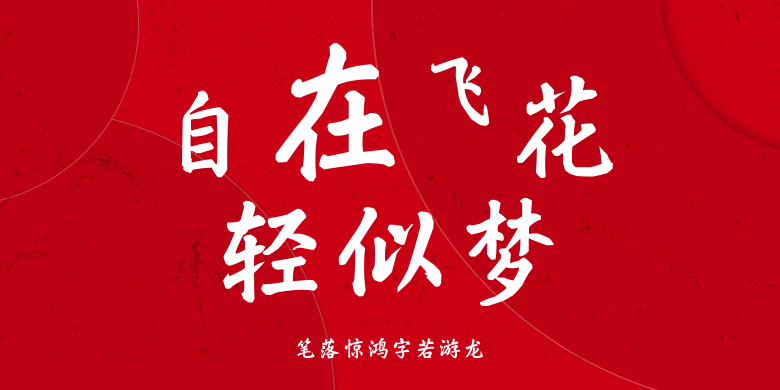
笔落惊鸿字若游龙
笔落惊鸿字若游龙,这款字体结构工整、笔画清晰,兼顾美观与易读性,适用于标题、正文、海报、包装、LOGO 等多种场景。字形优雅稳定,风格百搭耐看,适配日常排版与创意设计,让文字呈现更舒适、更具质感。笔落惊鸿字若游龙一笔一画,皆是细节,以均衡的比例、流畅的线条打造舒适视觉体验,字形端正大气,风格简约现代。无论是商业设计、品牌宣传还是日常排版,都能轻松驾驭,让文字更有格调与力量。笔落惊鸿字若游龙字体下载。